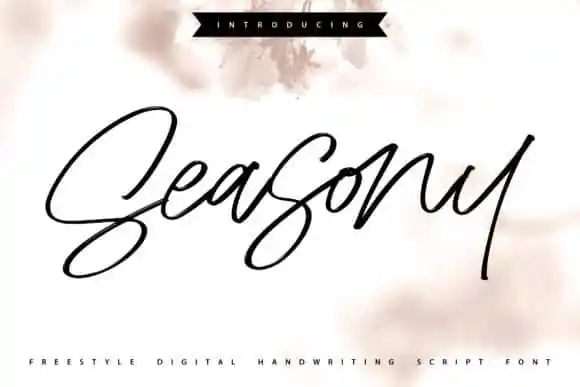
A ‘Seasony Script Font’ é uma escolha perfeita para designers que procuram uma fonte única e moderna para seus projetos visuais. Fabricada pelo designer Vunira, esta fonte elegante traz uma sensação de frescor ao seu trabalho, particularmente em criações como logotipos, identidades visuais e frases inspiradoras. Cada letra deste fonte apresenta um toque único e belo, proporcionando um toque autêntico e criativo a seus projetos. Composta por linhas levemente curvadas que se movem suavemente entre as letras, cada caracter tem a capacidade de transformar qualquer projeto em algo extraordinário e memorável. Em uma era onde a originalidade é cada vez mais valorizada, esta fonte oferece um toque especial para seus designes pessoais ou corporativos, garantindo que seu trabalho se destaque dos demais. Seja você um designer profissional ou iniciante, a ‘Seasony Script Font’ é certamente uma fonte indispensável no seu arsenal de recursos gráficos.